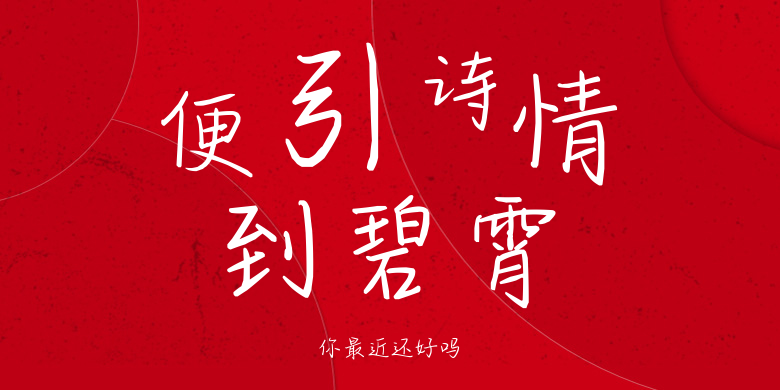
你最近还好吗
你最近还好吗,这款字体结构工整、笔画清晰,兼顾美观与易读性,适用于标题、正文、海报、包装、LOGO 等多种场景。字形优雅稳定,风格百搭耐看,适配日常排版与创意设计,让文字呈现更舒适、更具质感。你最近还好吗一笔一画,皆是细节,以均衡的比例、流畅的线条打造舒适视觉体验,字形端正大气,风格简约现代。无论是商业设计、品牌宣传还是日常排版,都能轻松驾驭,让文字更有格调与力量。你最近还好吗字体下载。